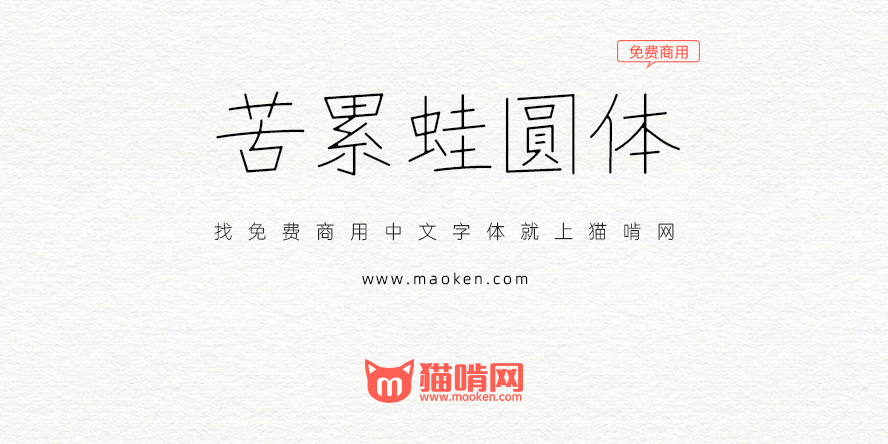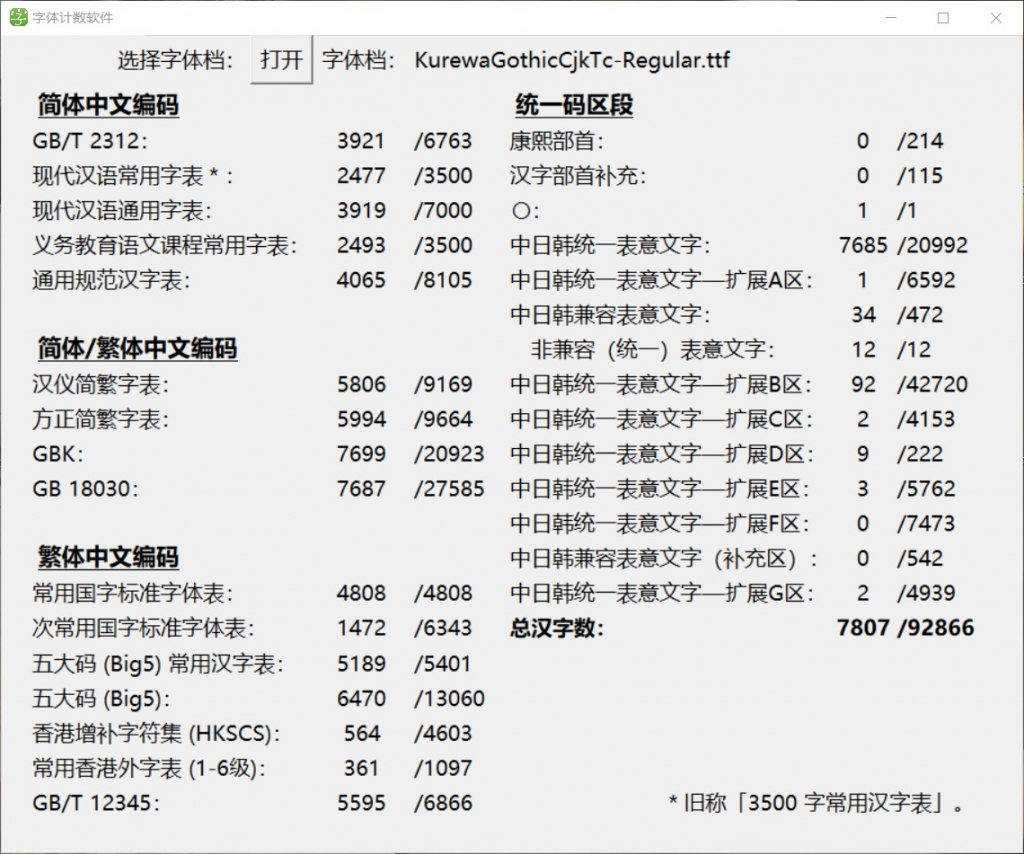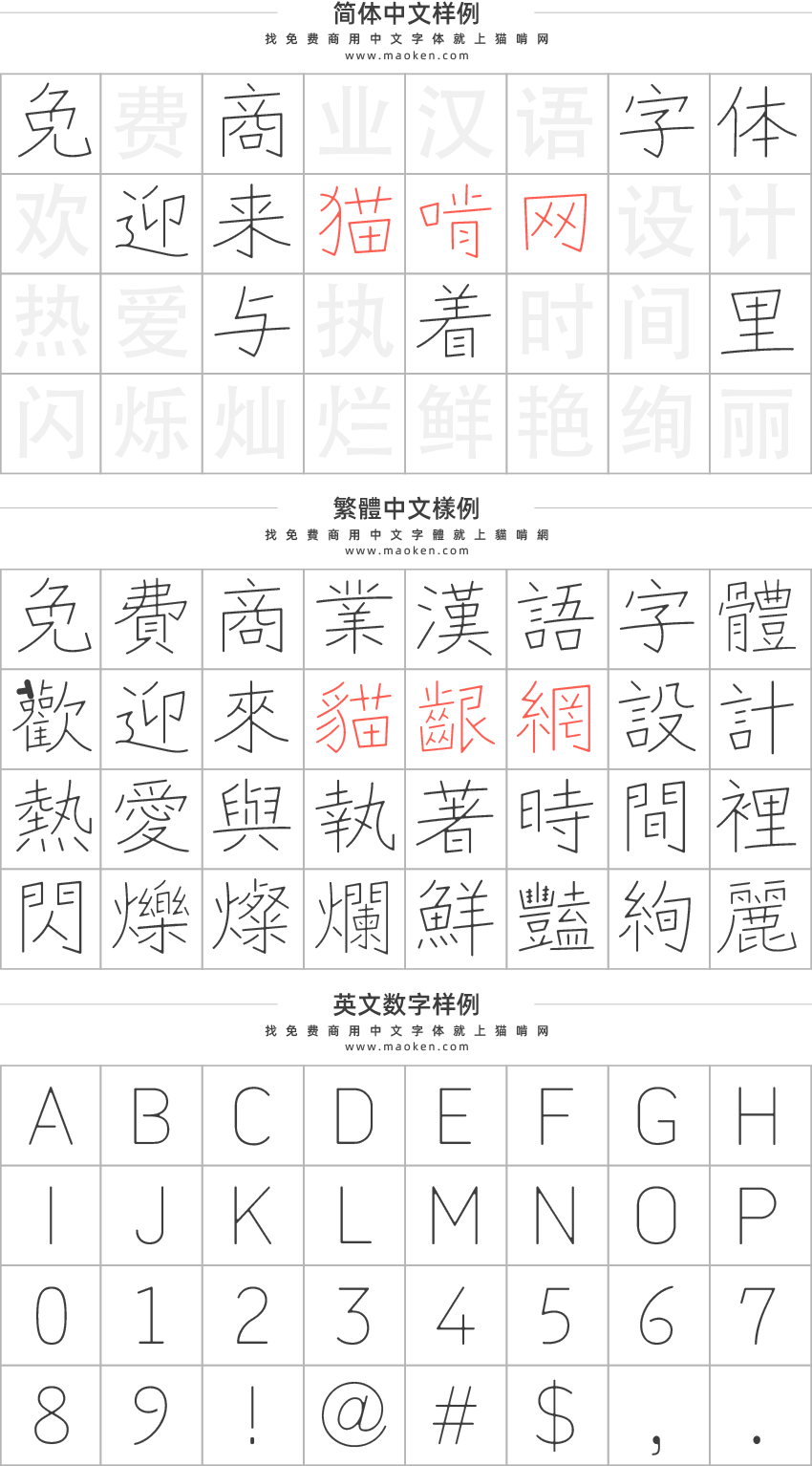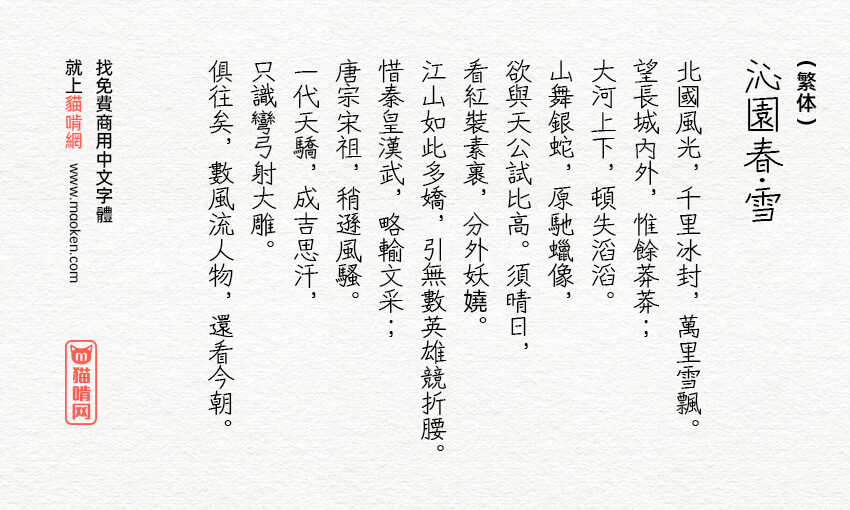
苦累蛙圆体是Zen红道手写字体的补字计画。与原作者的主要不同是修改编辑法、增加中文字、增加为5个字重、增加一些符号。可以免费公开,欢迎大家自由应用、自由优化、自由改作!
字体特色
特色1:开幕繁体中文字常用缺字缺欠
解决常用的中文口语用词,最多补了几句中文字,应该可以满足大缺的需求,比如:喵喵屌粿浓缩捂嘴憋闷尪孬憋。
- 附注1:因为是非专业级的补字,新加入的字在风格上,虽然尽力求满足,难免会与原作者一样有些或较丑。
- 附注2:原作者的孩子是使用日本写法,补的字现在是使用台标体,混搭起来会怪怪的,聊胜于无。
- 附注3:因为是第一次使用贝兹峰,所以很多字长的怪怪的,目前技术已经有提升,如果未来有空,再重做笔画歪扭扭扭的那些字。如果遇到太丑的字,欢迎留言,我会优先重做这些字。
- 附注4:CJK TC的「骨」字这个下面是肉不是月,修改会是大工程⋯⋯,暂时无法去解决。
特色2:5种字重(Style)
- Light
- DemiLight
- Regular (原作者的字重)
- Medium
- SemiBold
原作者的字重放在Regular字重里,透过程式自动产生Light、DemiLight、Medium、SemiBold 新的字重。
在ExtraLight和Light字重是把原本的Otsutome Font微微调细一点点。在Light的字重里,可能会因为笔划太细造成某些笔画消失。
在Medium和SemiBold的字重里,可能会因为笔划太粗造成某些笔画重叠难以识别,有粗体字的需求,可以先挑战使用SemiBold字重看看,如果发现效果不如预期,再改用Medium字重。
不能确定自动产生出来的字重里每一个都是完整的字,毕尽程式会误判是常有的事情,所以「不是在Regular字重」里的笔划可能会消失。
特色3:调整标点符号位置
原作者的全形标点符号针对日本做设计,调整为台湾常见的置中最佳。
特色4:增加闽南语和客语台湾中文字
特色5:调整商品写法
部份的文字,CJK TC/CJK JP 写法不同,所以保留原作者的CJK JP写法在CJK JP的版本里。